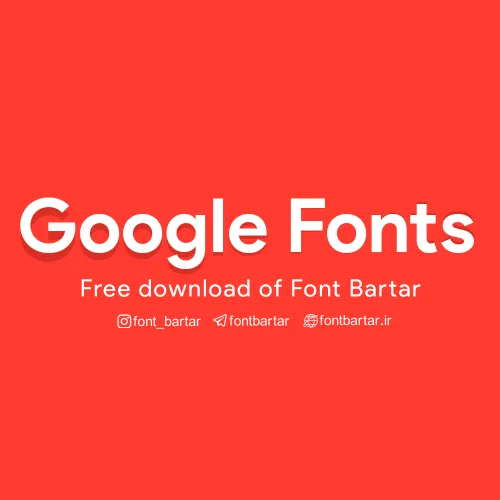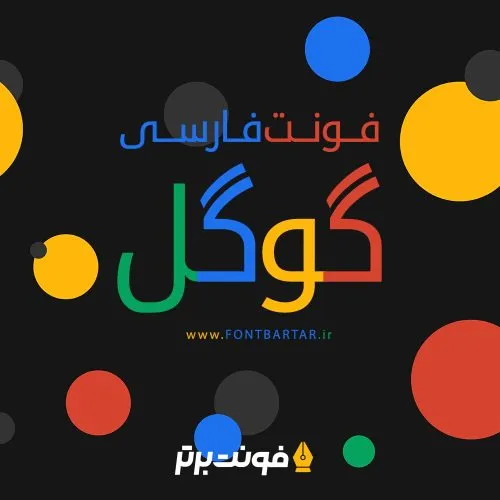
فونت لوگو گوگل – Google font
در این مطلب برای شما سروران گرامی فونت مورد استفاده کمپانی گوگل در لوگوی خود را آماده کرده ایم که بسیار کمیاب و همچنین بسیار کاربردی است فونت ساده با چینشی فوق العاده خاص و زیبا که مناسب طراحی های متریال و یا فلت می باشد ! البته نیاز به معرفی و یا توضیح اضافه نمی باشد چرا که مطمئنا در طول روز با این فونت چه در وبگردی و یا چه در کار با نرم افزار های کمپانی بزرگ گوگل با این فونت برخورد کرده ایم و تقریبا همه این فونت را می شناسند.
فونت لوگو گوگل مورد استفاده برای:
- طراحان وب سایت و گرافیست های خلاق می توانند از این مجموعه زیبا فونت در طراحی پروژه های تبلیغاتی و تجاری خود کمک بگیرند.